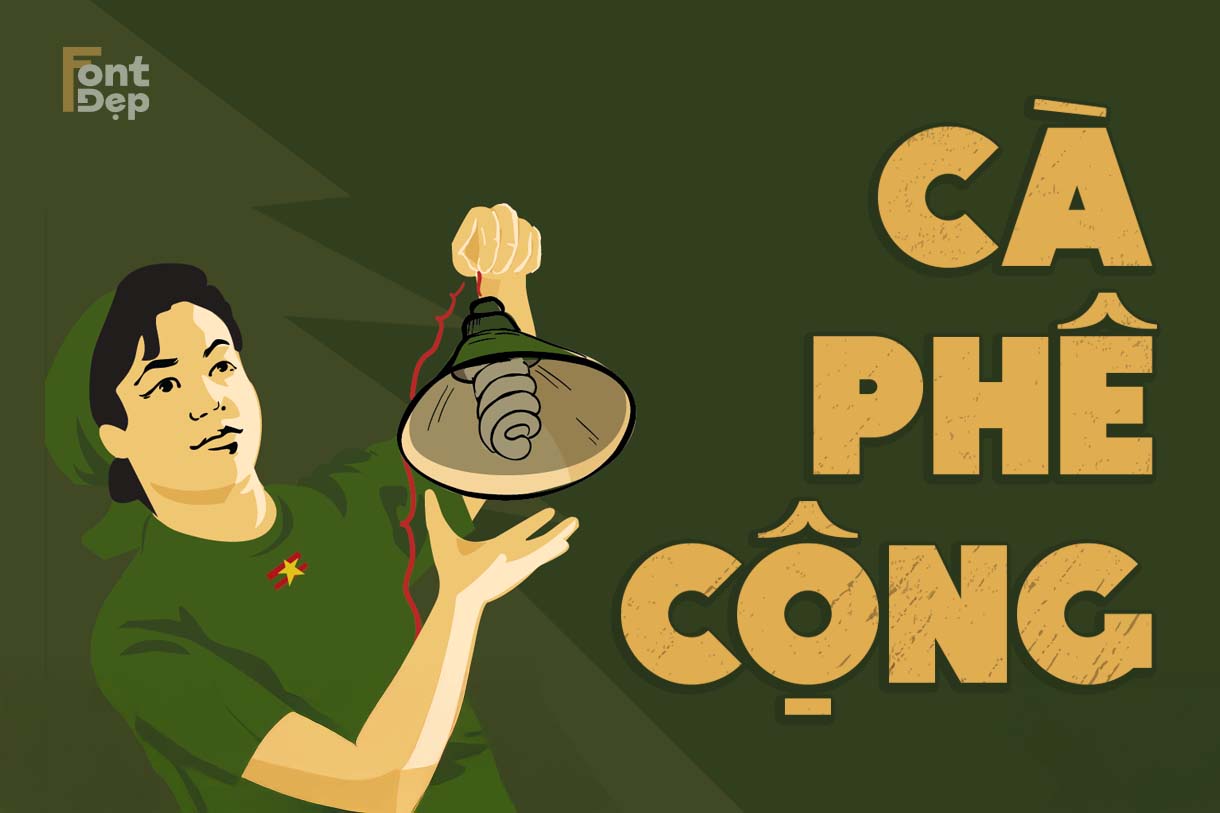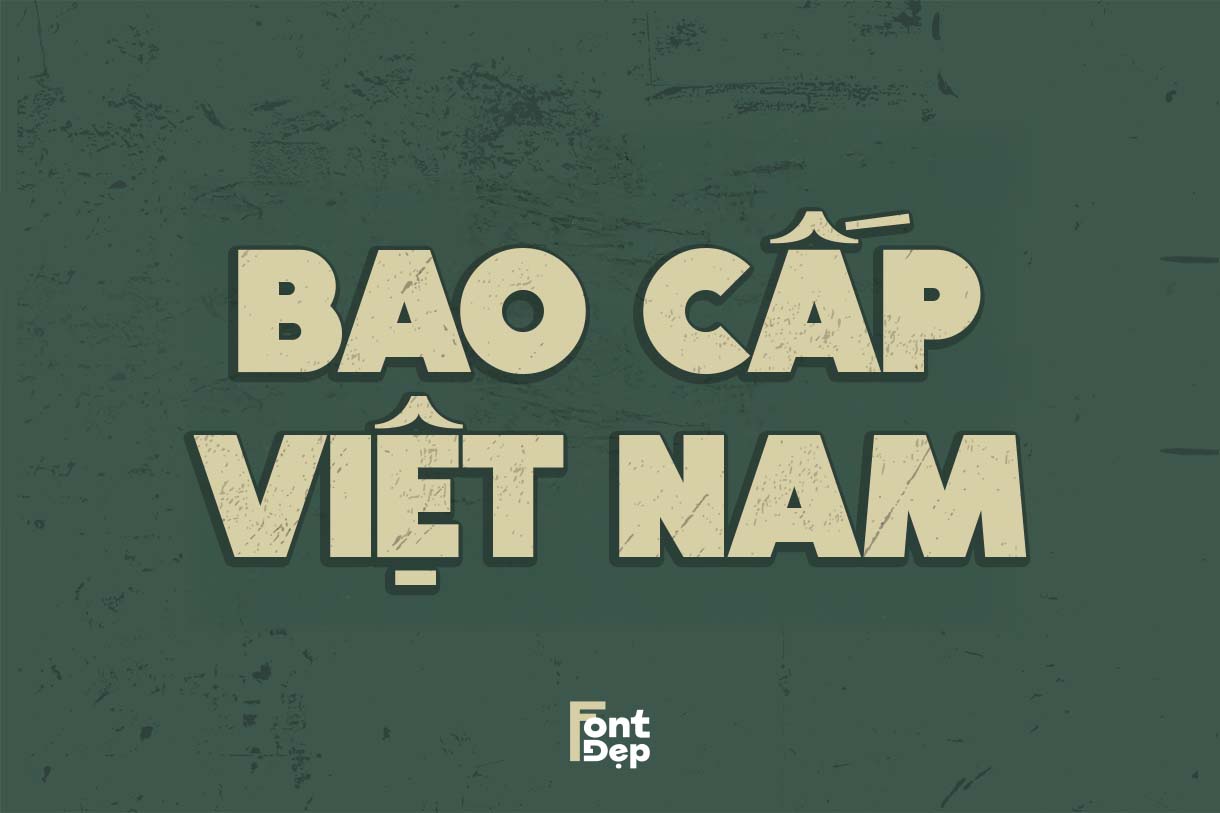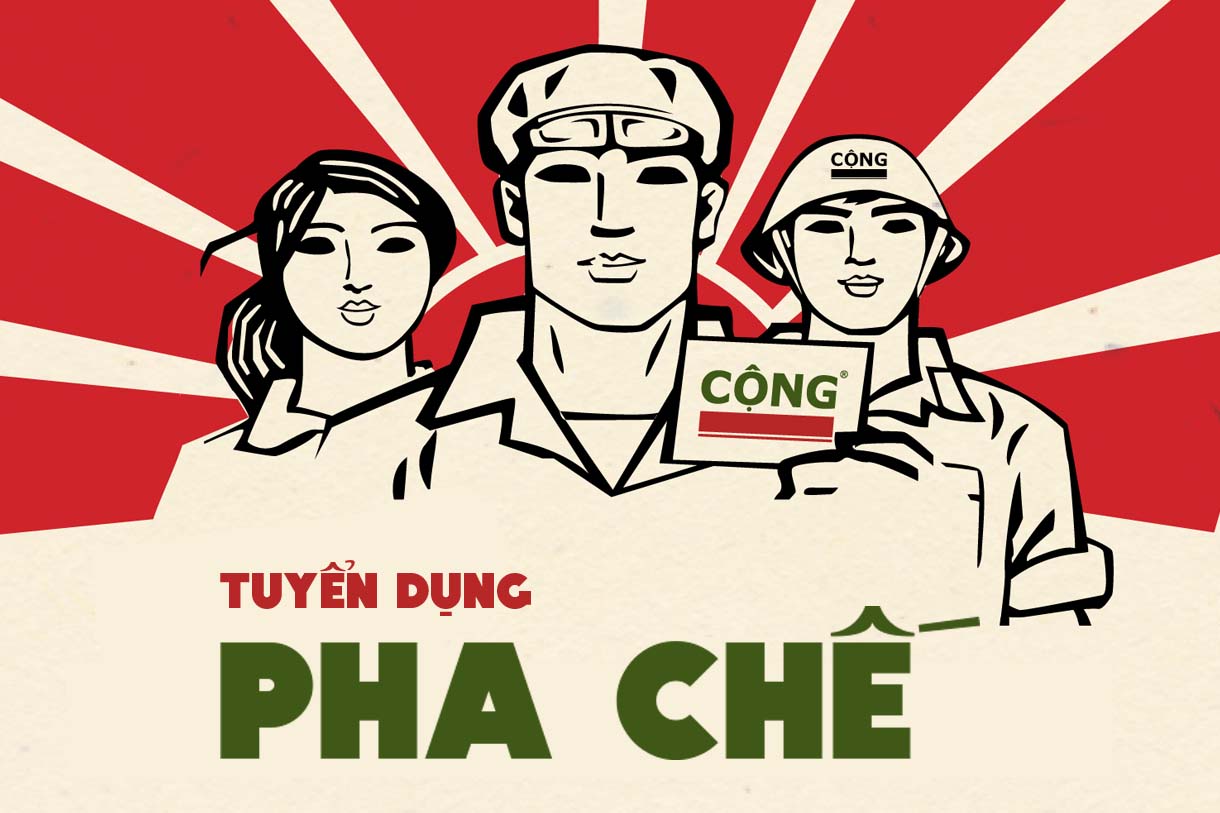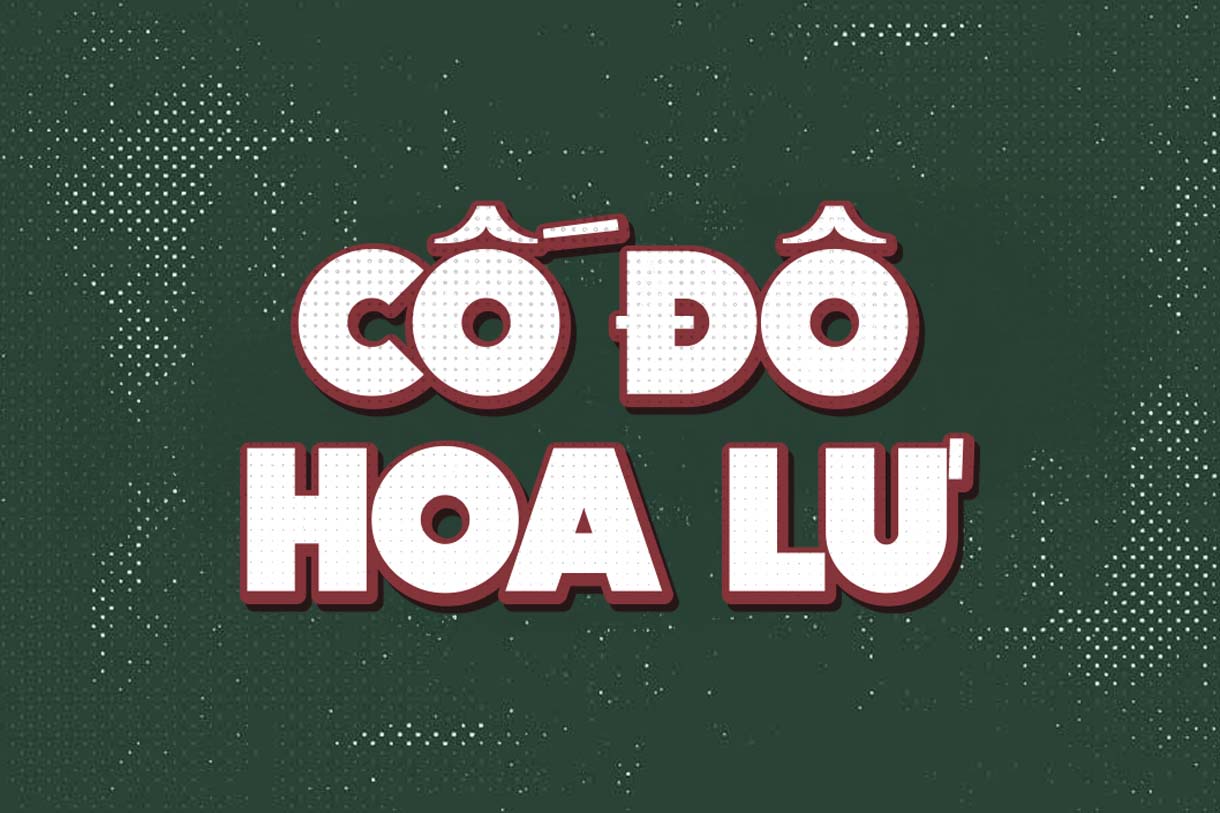
Tải Xuống Font Chữ Hoài Cổ Xưa TH Colombo Sans – Việt Hóa Thời Bao Cấp
Trong thời buổi thiết kế hiện đại, nơi mọi thứ ngày càng tối giản và số hóa, thì những giá trị hoài cổ lại có một sức hút đặc biệt. "Font chữ hoài cổ" là thuật ngữ chỉ những kiểu chữ gợi nhớ về quá khứ – có thể là những thập niên 60–80, thời kỳ bao cấp, hay các biển hiệu, áp phích xưa. Không đơn thuần là một bộ ký tự, các font chữ này mang theo cảm xúc, kỷ niệm và cả văn hóa. Chính điều đó khiến font chữ xưa trở thành một xu hướng quay lại mạnh mẽ trong thiết kế hiện đại, bởi nó không chỉ đẹp mà còn chạm được đến chiều sâu ký ức.
Bộ font Colombo Sans được thiết kế bởi Borutta Group, một studio thiết kế đến từ Ba Lan (Poland). Đây là nhóm đứng sau nhiều dự án font chữ mang tính hình học và hiện đại, với phong cách pha trộn giữa retro, editorial và sáng tạo đương đại.
• Tên đầy đủ: Colombo Sans Typeface
• Tác giả: Borutta Group
• Nguồn gốc: Ba Lan
• Phong cách thiết kế: Sans-serif, mang hơi hướng cổ điển pha hiện đại.
TH Colombo Sans – Phông chữ hoài cổ thời bao cấp đã Việt hóa hoàn chỉnh
TH Colombo Sans là một trong những font chữ điển hình cho phong cách thời bao cấp. Được Việt hóa hoàn chỉnh bởi Phạm Sơn (admin Fontdep.vn), bộ font hỗ trợ đầy đủ tiếng Việt với các dấu thanh và ký tự đặc biệt. Font thuộc nhóm sans-serif, không chân, nhưng lại gợi cảm giác rất cổ điển, giống như những tiêu đề báo chí, áp phích tuyên truyền hay các tài liệu hành chính của những năm 1975–1990.
Đặc điểm thiết kế nổi bật của TH Colombo Sans
TH Colombo Sans sở hữu kiểu dáng sans-serif đậm nét, các chữ cái có độ cao vừa phải, tạo cảm giác chắc chắn nhưng không cứng nhắc. Các nét chữ dày vừa đủ để hiển thị tốt ở cả kích thước lớn và nhỏ, rất dễ đọc. Chính sự cân bằng giữa tính hiện đại và nét hoài cổ đã giúp TH Colombo Sans trở nên linh hoạt và nổi bật. Khi nhìn vào font, người xem có thể dễ dàng liên tưởng đến các bìa sách, bao bì sản phẩm, hoặc tờ rơi thời bao cấp với tinh thần mộc mạc, gần gũi.
Ứng dụng của TH Colombo Sans
TH Colombo Sans là lựa chọn lý tưởng cho các poster quảng cáo mang phong cách xưa, banner triển lãm nghệ thuật, hoặc bao bì sản phẩm thủ công. Bạn cũng có thể sử dụng font này cho nhận diện thương hiệu của quán cà phê vintage, nhà hàng theo phong cách Đông Dương hoặc các ấn phẩm truyền thông mang hơi thở văn hóa Việt.
Lưu ý khi sử dụng font hoài cổ để tránh bị “cũ kỹ”
• Ghép font hợp lý: dùng TH Colombo Sans làm tiêu đề, kết hợp font sans đơn giản cho phần thân bài.
• Sử dụng màu sắc vintage như nâu, đỏ đất, vàng nhạt để tôn lên chất cổ điển.
• Tránh lạm dụng – chỉ nên dùng trong những thiết kế cần truyền tải cảm xúc hoặc giá trị truyền thống.
Tổng kết – Từ một font xưa đến biểu tượng văn hóa
TH Colombo Sans không chỉ là một font chữ, nó là chiếc cầu nối giữa quá khứ và hiện tại. Trong mỗi đường nét chữ đều gợi nhắc đến một thời kỳ khó quên của người Việt – nơi sự mộc mạc, giản dị lại trở thành một phong cách riêng biệt. Với độ hoàn thiện cao, hỗ trợ tiếng Việt đầy đủ và tinh thần hoài cổ rõ ràng, font này xứng đáng có mặt trong bộ sưu tập của bất kỳ designer yêu cái đẹp mang tính di sản.